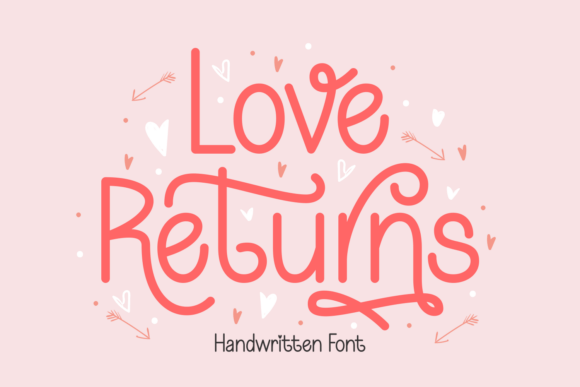
Love Returns
Пошук відповідних елементів дизайну може бути складним, але Love Returns пропонує виняткову колекцію, яка миттєво покращить вашу роботу.
Створений з високою точністю, Love Returns забезпечує чисті вектори, плавну типографіку та комерційну ліцензію для вашого спокою.
Незалежно від того, чи створюєте ви продукти POD (друк на вимогу), весільні запрошення або графіку для соціальних мереж, Love Returns стане ідеальним вибором.